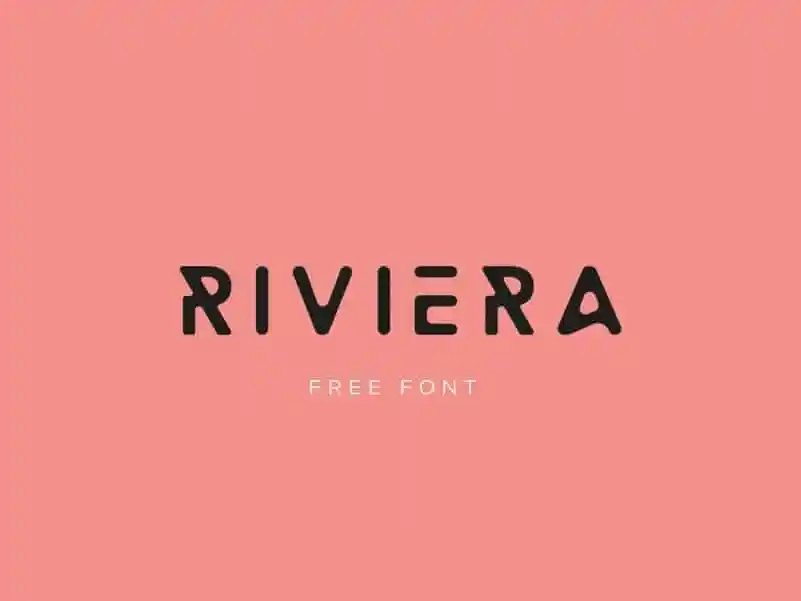
Riviera Display Font – Download Grátis
A Riviera Display Font é uma opção única para designers gráficos que desejam dar vida a seus projetos com um estilo moderno e arrojado. Ela surge como um revolucionário elemento na sua biblioteca de fontes, oferecendo um visual inovador e versátil. Os detalhes cuidadosamente concebidos por Johann Darcel Studio garantem que Riviera seja perfeito para headlines, logomarcas e materiais de propaganda. Suas linhas fluidas e formas geométricas atingem a essência do design atual. A fonte é uma maneira fresca e singular de destacar seus trabalhos nas plataformas digitais ou impressa. Fique pronto para incorporá-la à sua biblioteca de fontes, tornando-a um elemento essencial no seu arsenal criativo.